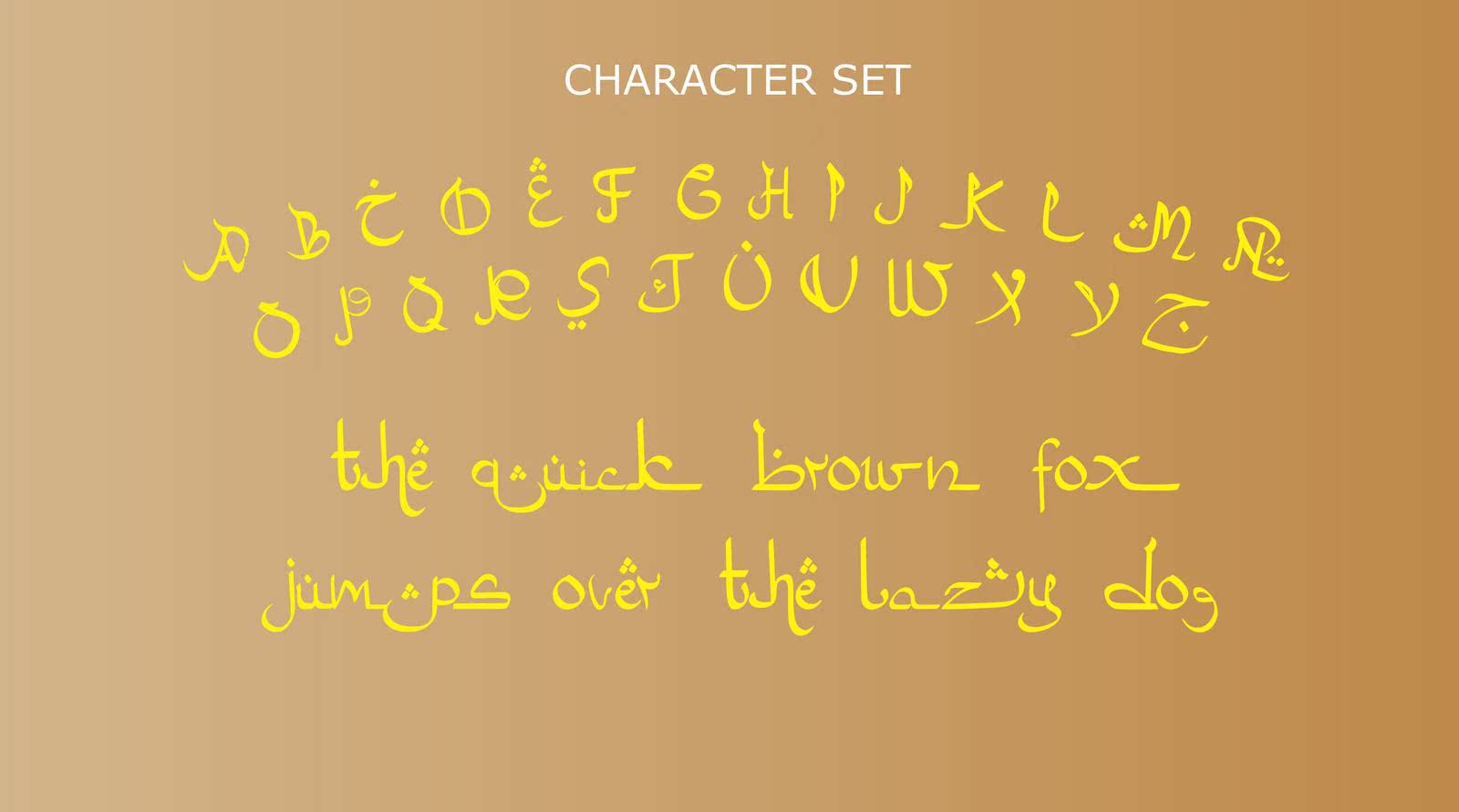
Sultanaisanarabicfauxlang字体。此字体非常适合您的项目。如广告牌、排版、海报、传单、标题、广告、您的产品、t恤、商品、甚至是书籍封面和其他!Sultanaisanarabicfauxlang字体。此字体非常适合您的项目。如广告牌、排版、海报、传单、标题、广告、您的产品、t恤、商品、甚至是书籍封面和其他!